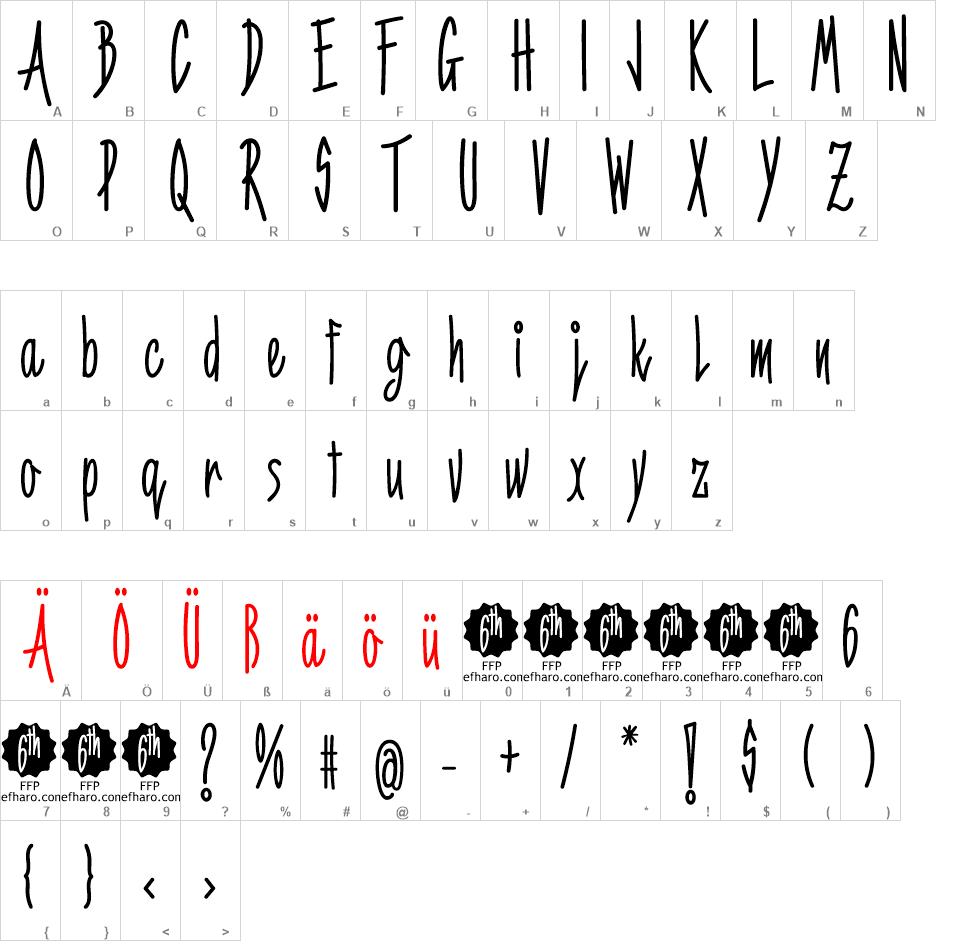
6th Aniversario
6. Aniversario ist eine abgerundete komprimierte Typografie, handschriftlich und elegant, perfekt zum Verfassen von guten Werbetexten im Grafikdesign von Postern, Flyern oder Publikationen im Allgemeinen, wo Platzersparnis und Lesbarkeit gefordert sind. Enthält das Bitcoin-Symbol.
Bitcoin-Symbol (Ligaturen): b #
- OpenType-Funktionen: Brüche, alternative Anmerkungsformen, alle Alternativen, Hochstellung, Vorgesetzte, Zerschlagte Null, Superior-Buchstaben, lokalisierte Formen, Zahlen-Kapitälchen, Inferiors, Inferioren, Diskretionsligaturen, Numeratoren, Standardligaturen, Tiefstellung, erweiterte Brüche, Ordinalzahlen, Denominators, Oldstyle-Figuren, historische Formen.